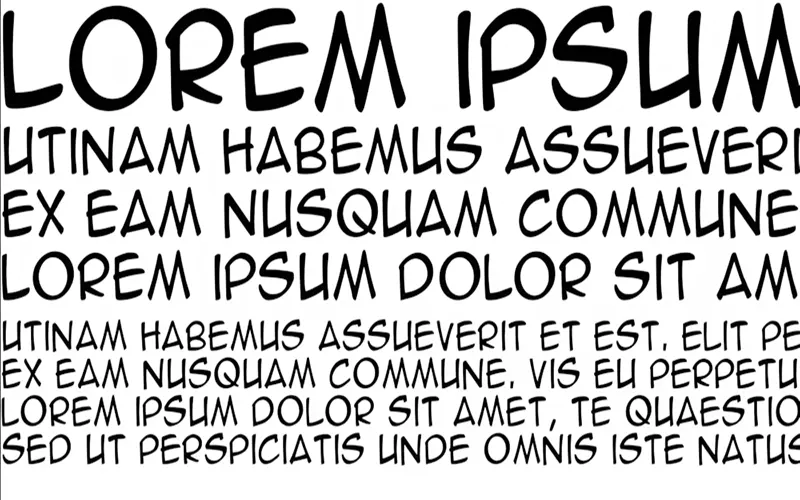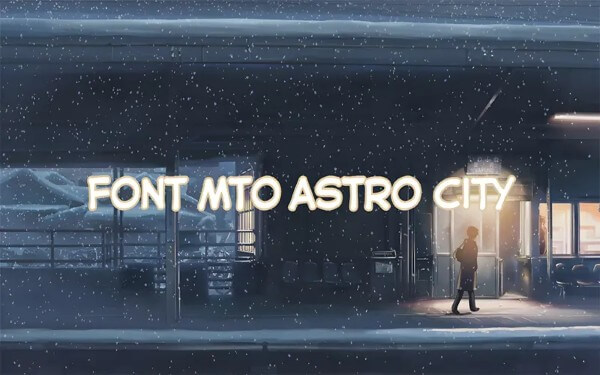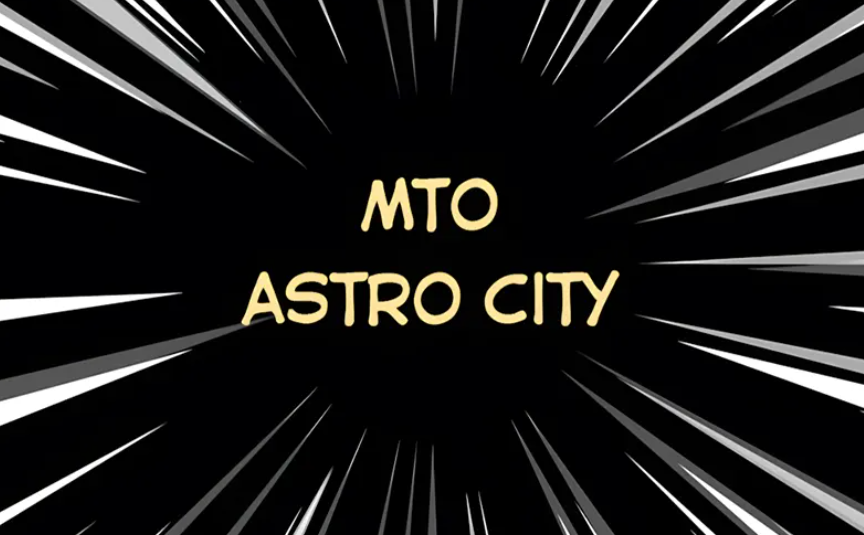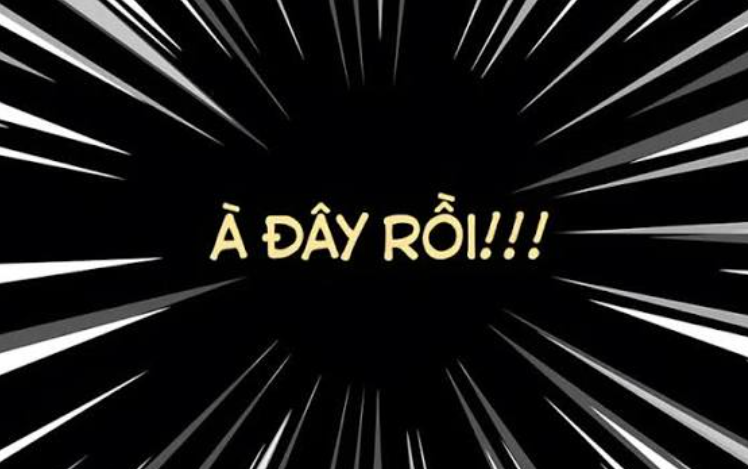
Font MTO Astro City Việt hóa là bộ phông chữ thuộc dòng Display Action mang phong cách khoa học viễn tưởng (Sci-fi) và tốc độ, nổi bật với cấu trúc chữ nghiêng sắc sảo, dứt khoát đậm chất hành động. Được tinh chỉnh hoàn thiện hệ thống dấu tiếng Việt bởi nhóm MTO, phông chữ này mô phỏng hoàn hảo các tiêu đề truyện tranh manga hành động, poster phim siêu anh hùng và giao diện không gian tương lai. Doozypack.vn cung cấp link tải trọn bộ chuẩn kỹ thuật, giúp bạn sở hữu font MTO Astro City Italic cá tính này mà không lo gặp bất kỳ lỗi hiển thị dấu thanh nào khi thiết kế in ấn bao bì.
Đặc điểm thẩm mỹ độc đáo của bộ font MTO Astro City
MTO Astro City không đi theo sự ngay ngắn truyền thống; nó mang đến một ngôn ngữ thị giác đầy tốc độ, tái hiện trọn vẹn những đường nét cắt xẻ mạnh mẽ của thế giới tương lai.
Phong cách Sci-fi Action Italic đầy tốc độ và mạnh mẽ
Đặc trưng lớn nhất của Font MTO Astro City Việt hóa là góc nghiêng độc đáo kết hợp cùng cấu trúc chữ hình học sắc lẹm. Từng ký tự được vuốt nhọn ở các góc, tạo cảm giác chuyển động về phía trước như những vệt sáng xé gió trong các cảnh chiến đấu không gian. Phong cách này mang lại sự kịch tính, uy lực và cực kỳ thu hút đối với cộng đồng yêu thích truyện tranh hành động và công nghệ viễn tưởng.
Góc nghiêng sắc sảo mang hơi thở tương lai
Các biến thể như Font MTO Astro City nghiêng hay bản Italic sở hữu góc nghiêng được tính toán chuẩn xác, giúp tiêu đề bản thiết kế giữ được sự đĩnh đạc nhưng vẫn tràn đầy năng lượng bùng nổ. Khi đặt làm tiêu đề trên bao bì, phông chữ này sẽ ngay lập tức tạo ra điểm nhấn thị giác vô cùng sắc sảo.
Ưu điểm nổi bật của bản MTO Font Việt hóa
Khi ứng dụng các phông chữ hành động quốc tế vào thị trường trong nước, sự chỉn chu về dấu câu là yếu tố quyết định đến tính chuyên nghiệp của ấn phẩm:
- Khắc phục triệt để lỗi dấu tiếng Việt: Phiên bản font Việt hóa Manga MTO Astro City đã được đội ngũ thiết kế trau chuốt thủ công từng dấu câu. Các dấu sắc, huyền, hỏi, ngã, nặng được vẽ nghiêng đồng điệu cùng thân chữ gốc, không gây cảm giác chắp vá hay đè nét làm mất tính thẩm mỹ hành động.